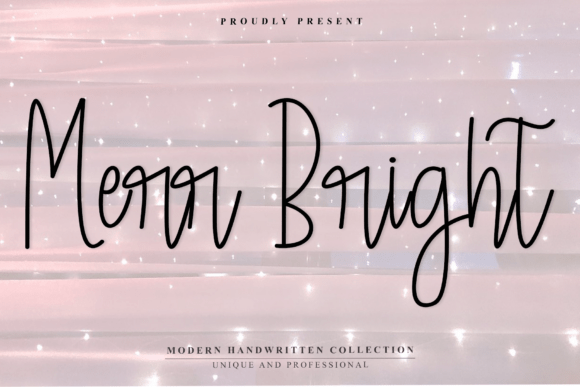
Merr Bright Font
Encontrar los elementos de diseño adecuados puede ser un desafío, pero Merr Bright Font ofrece una colección excepcional que eleva tu trabajo al instante.
Elaborado con precisión, Merr Bright Font proporciona vectores limpios, tipografía suave y una licencia comercial para tu tranquilidad.
Ya sea que estés creando productos POD (impresión bajo demanda), invitaciones de boda o gráficos para redes sociales, Merr Bright Font es una opción ideal.